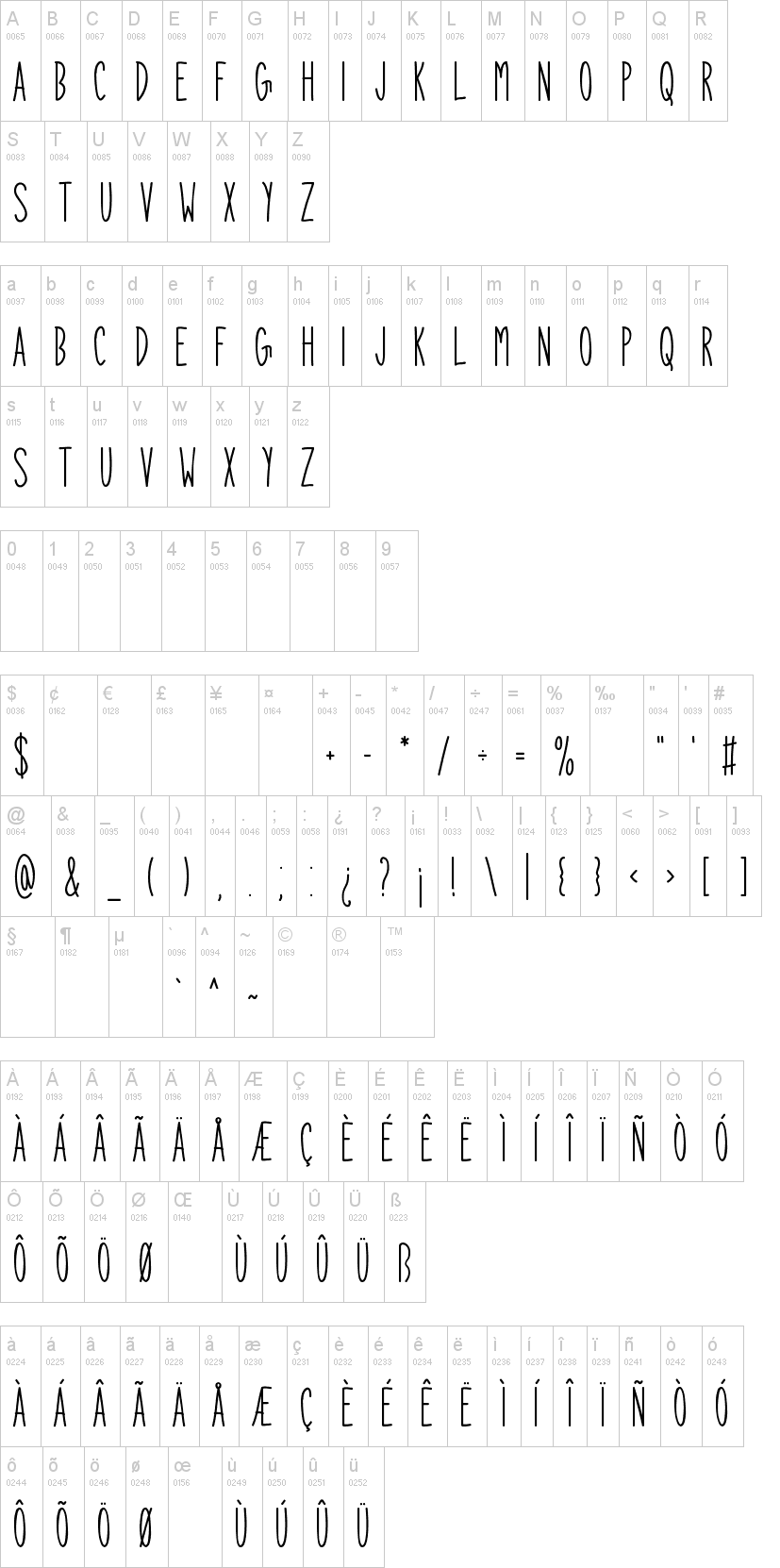
Dokrak 字体是一种免费的泰国字体,由 Thai Linux Working Group 开发。它包含了泰国语的所有字符,包括泰文、阿拉伯数字和英文字母。该字体具有较高的可读性和清晰度,适用于印刷和数字文档。Dokrak 字体还有多种字重可供选择,包括粗体、斜体和常规字体,可以满足不同排版需求。该字体目前可在许多网站上进行免费下载和使用。内容介绍
Dokrak是一款非常不错的手写艺术字体,具有很好的视觉感,适合于文化类的宣传设计、商业类品牌的广告和产品包装设计以及个性化文字排版等较多场景。